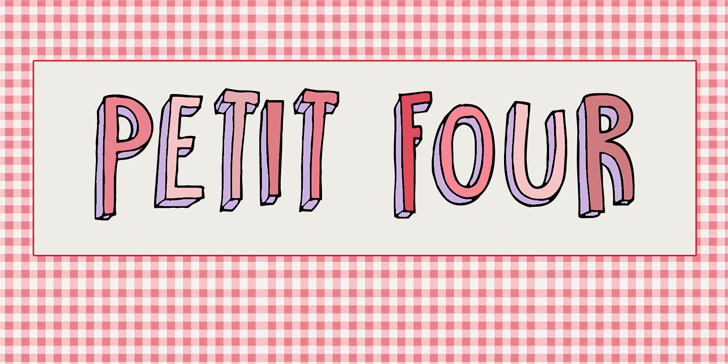
DK Petit Four é uma elegante e curvilínea fonte display desenvolvida pelo designer Hamilton. Suave e envolvente, esta fonte não apenas se destaca nas aplicações digitais como também ganha vida no papel impresso. Seu design fluido e delicado torna-a ideal para cabeçalhos de sites, gráficos visuais e até mesmo selos ou cartões-postais personalizados. Completamente criada em uma versão demo com funcionalidades mínimas, DK Petit Four é gratuita apenas para uso pessoal. Para fins comerciais, por favor compre a versão completa que inclui kerning (ajuste entre letras), direitos de armazenamento e todas as gilis (caracteres) e extras disponíveis em seu site oficial: hanodedfonts.com. Não use esta fonte em jogos, aplicações ou software. Para qualquer uso comercial, é importante verificar os termos detalhados fornecidos pelo designer. Se você quiser adquirir um licenciamento para usar na indústria de jogos ou softwares, acesse o site oficial do Hamilton no www.hanodedfonts.com.